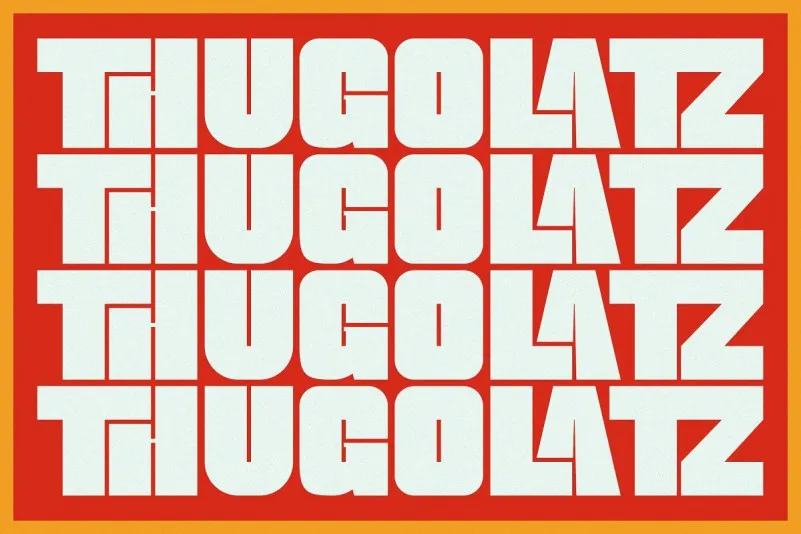
Thugolatz Font
A Thugolatz Font é uma opção atraente para quem busca um estilo bold e moderno para suas criações digitais. Inspirada na tipografia do título de postergadores esportivos, essa fonte é projetada com uma intensidade única, que vai elevar qualquer projeto. O designer 99designs atendeu aos detalhes da tipografia, considerando os tons e densidades dos glíferos e adicionou ligaturas para garantir o encanto singular do design. Esta fonte é perfeita tanto para uma paleta de tipos moderna quanto para um projeto em que deseja destacar sua mensagem. Seja você criando materiais publicitários, projetando logotipos ou simplesmente buscando aperfeiçoar suas criações digitais, esta font pode ser um aliado valioso no seu arsenal visual.